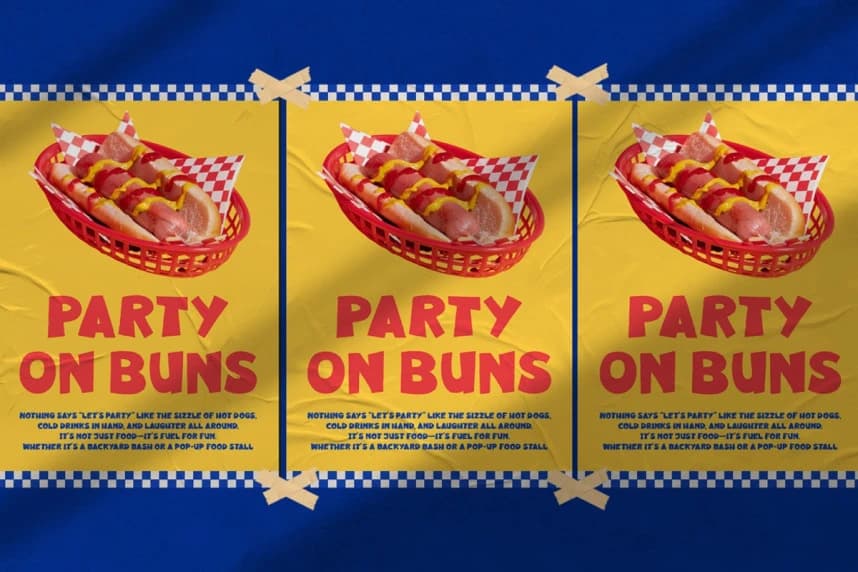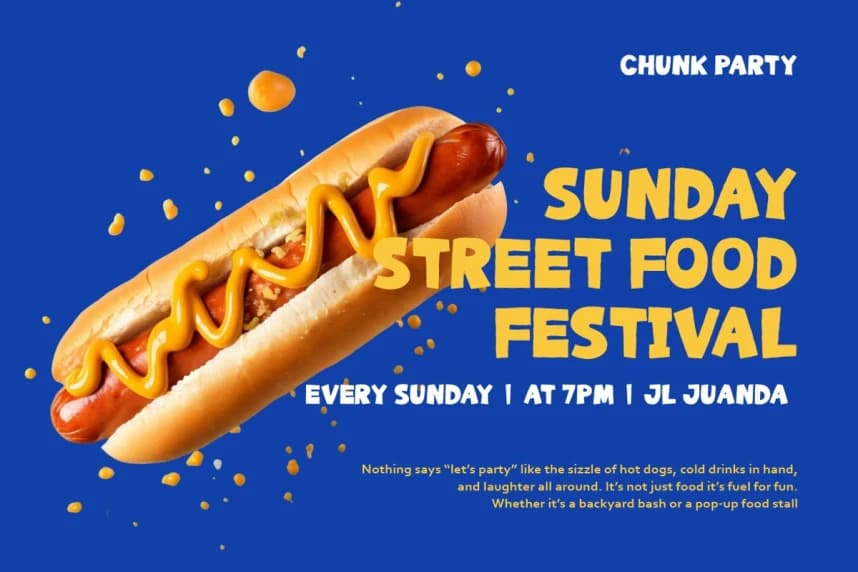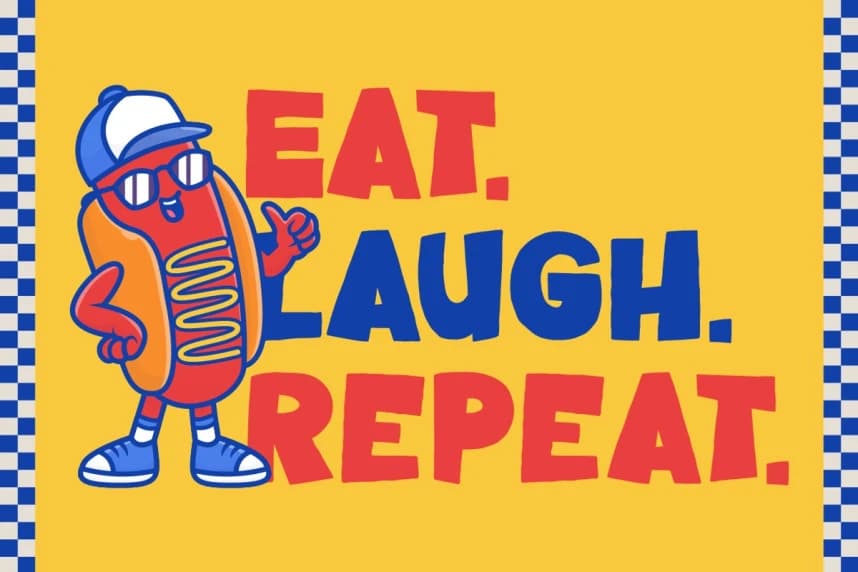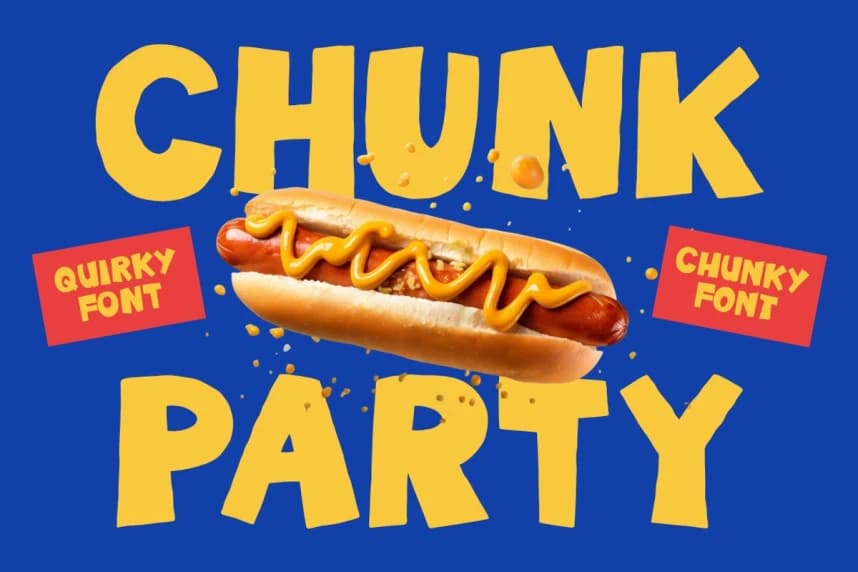
Chunk Party Font
Chunk Party Font, her tasarıma tat ve kişilik katıyor. Font, kalın ve düzensiz harf biçimlerine ve eğlenceli kenarlara sahip olup, canlı ve dinamik bir görünüm yaratır. Her bir karakter kalın ve iri olup, el yapımı bir görünüm sunar.
Chunk Party Font her tasarıma tat ve kişilik katıyor. Yazı tipi, kalın ve düzensiz harf biçimlerine sahip olup oyunlu kenarlarıyla canlı ve dinamik bir görünüm yaratır. Her karakter kalın ve tombul, el yapımı bir görünüm sağlar.